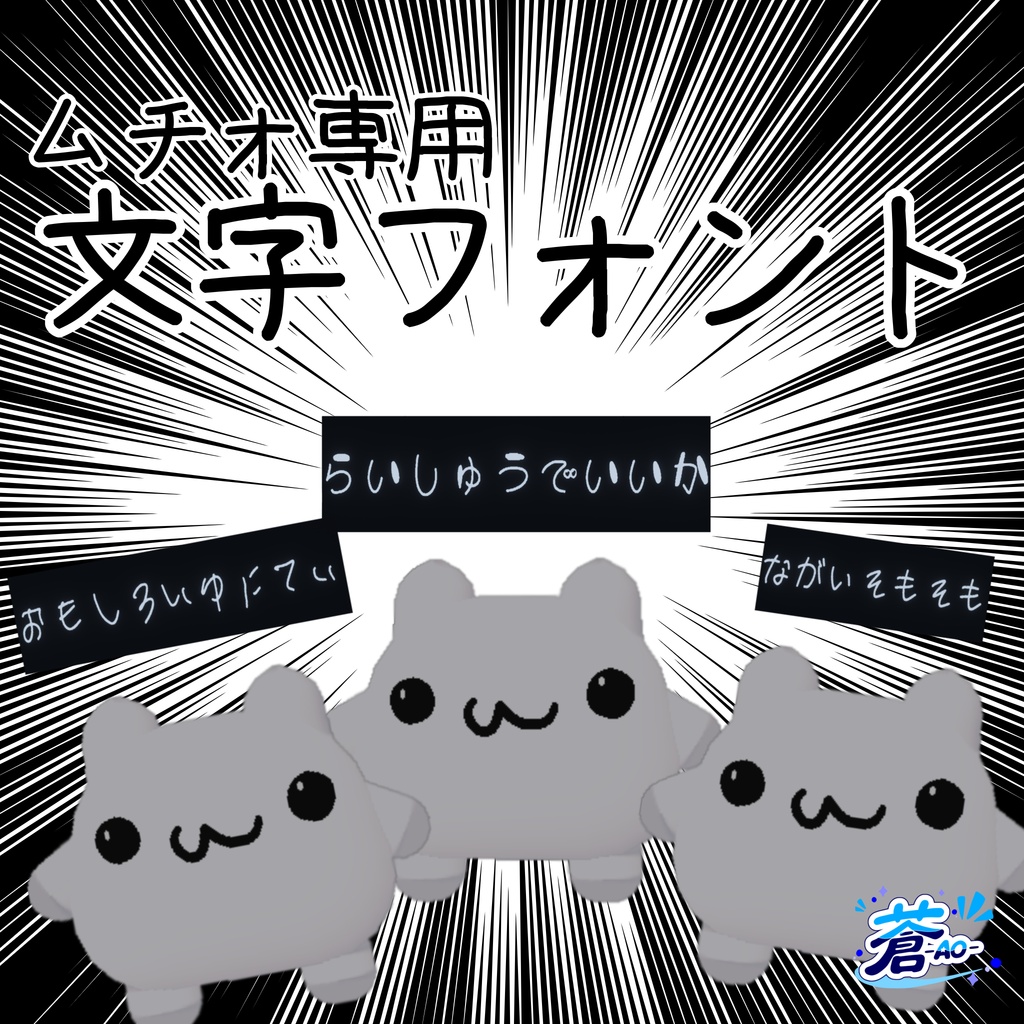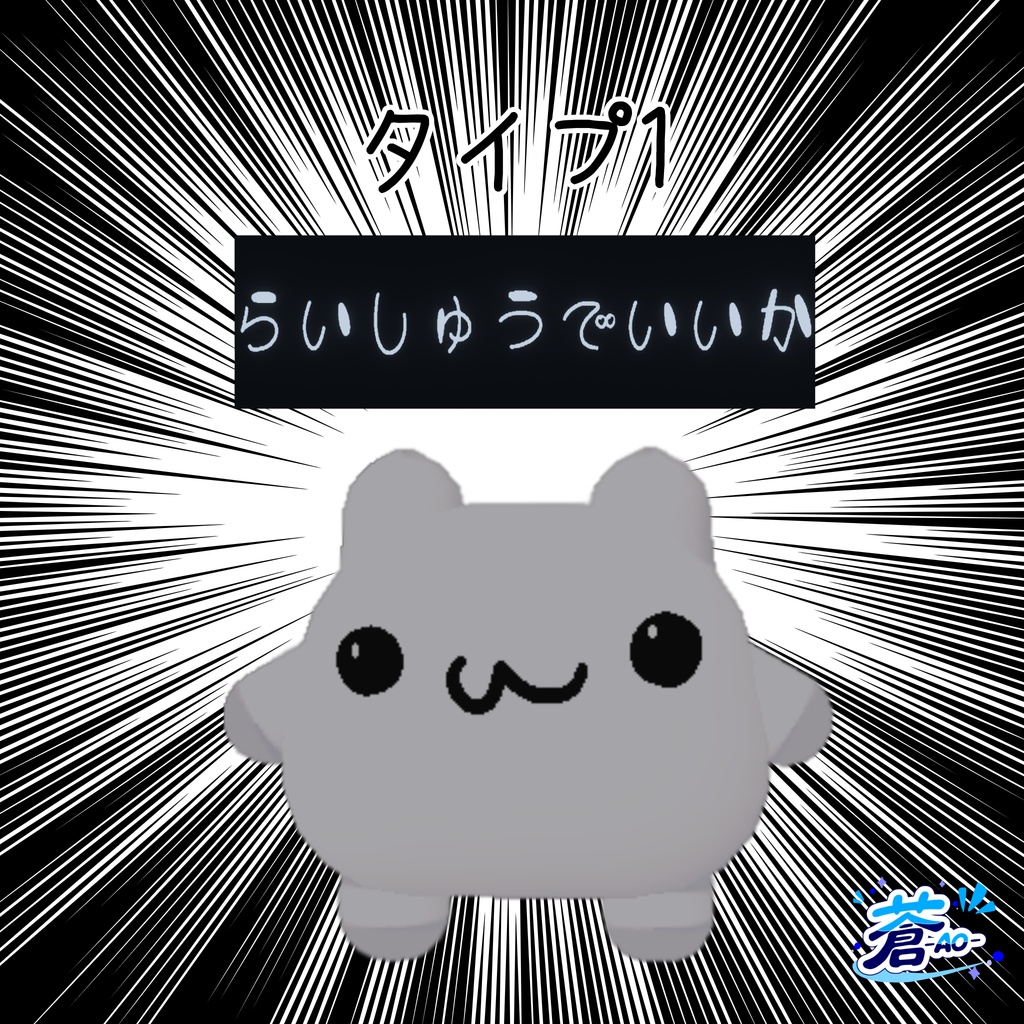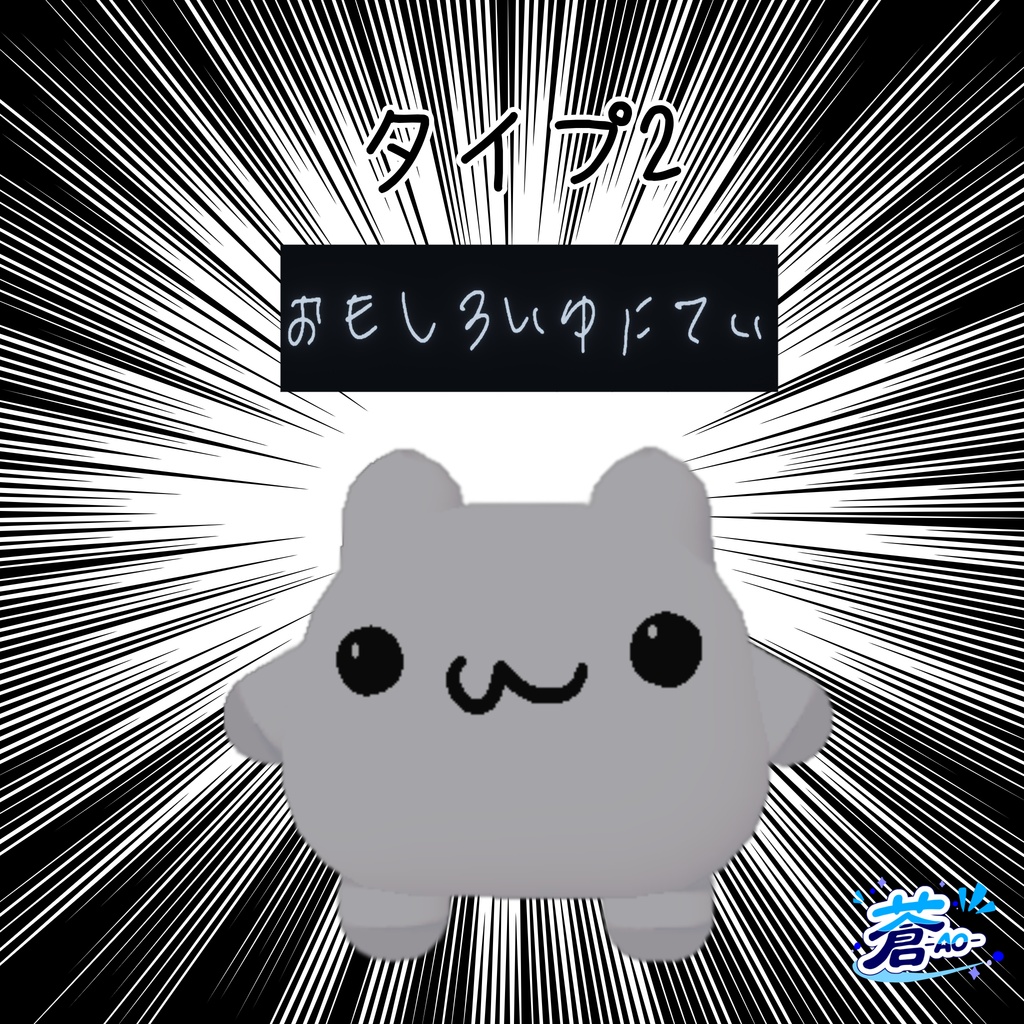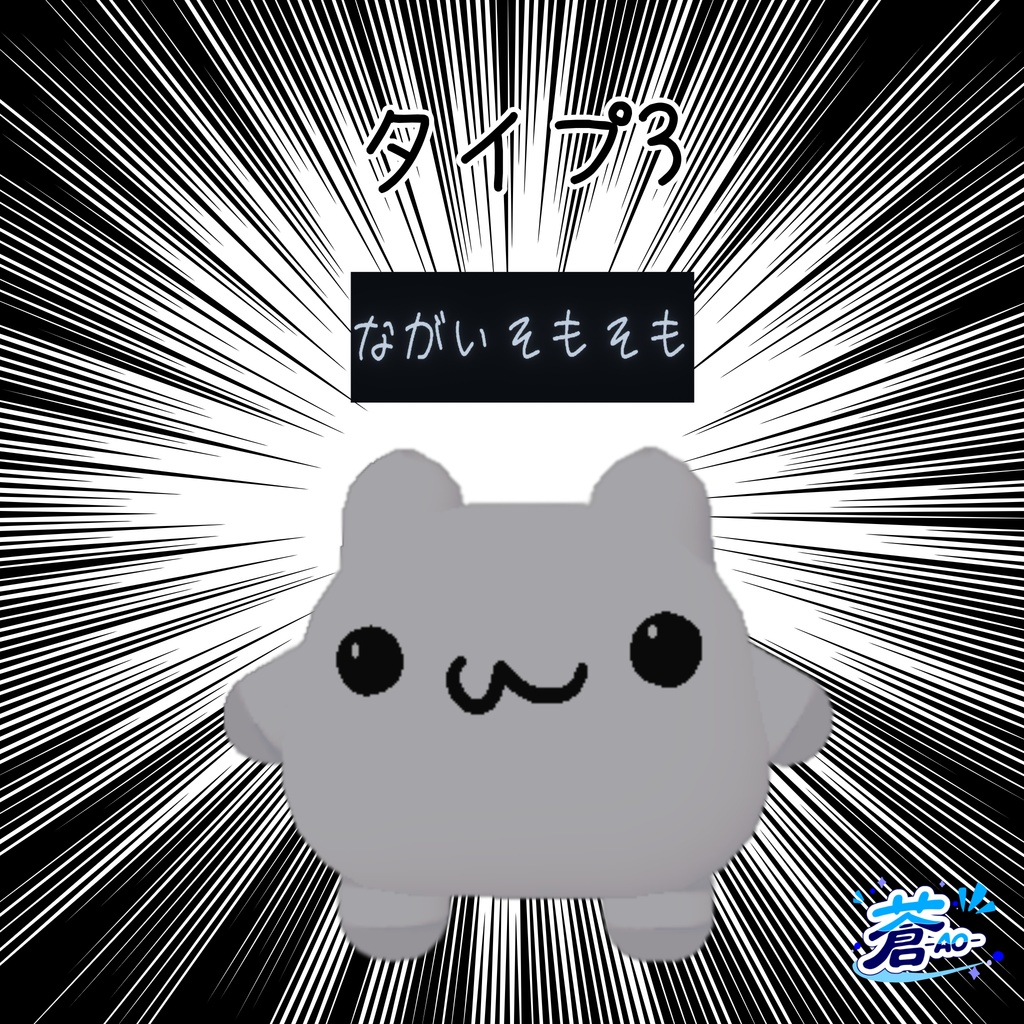
【ムチォ専用】文字フォント
対応アイテム 【言葉をおぼえる】なんかしゃべるペット?「ムチォ」【MA対応】 https://booth.pm/ja/items/8657397 自分用にムチォのしゃべる文字フォントを作りました。 変えたい人いれば.................. ☆タイプ1 かわいい系の文字 ☆タイプ2 汚い文字(利き手じゃない方でかきました) ☆タイプ3 自分自身の文字 です。 各ファイルに画像付きの説明書付きです!! 好きなものをご自由にどうぞ ☆-------------------------------------------------------------------------------------☆ アイテム本体は付属しておりません。 ダウンロード商品の特性上、交換や返金、返品につきましては対応致しかねます。 当モデルを使用して発生した、いかなるトラブルも当方は一切責任を負いません。 《許可》 ☆色改変 ☆配信、動画での使用可能 《禁止》 ☆テクスチャの再配布、再販売 ☆政治的、宗教的利用 ☆作者、その他関係者に迷惑のかかる使用 ☆公序良俗に反する使用 ご不明な点や不具合等ございましたら、BOOTHのメッセージにてご連絡下さい。 BOOTH https://aotokoakumakun.booth.pm/